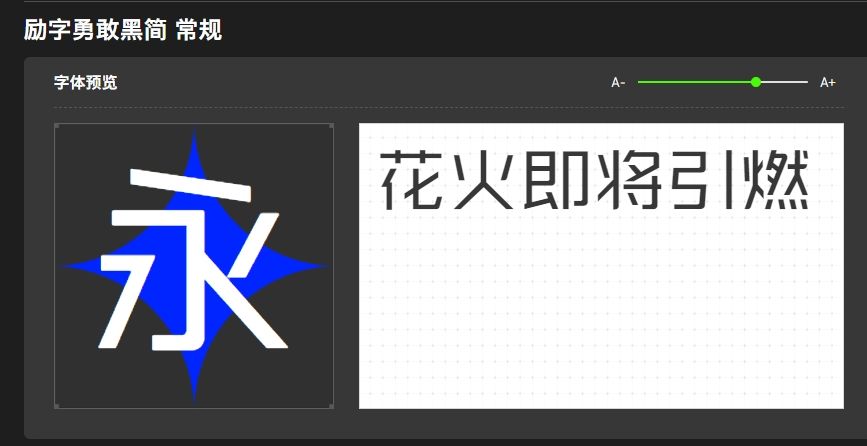
在品牌建设和推广过程中,字体的选择至关重要。一款合适的字体不仅能够准确传达品牌的形象和价值观,还能够增强品牌的识别度和记忆度。今天,就为大家推荐几款品牌都在使用的经典字体,为你的品牌设计提供灵感和参考。
励字励倩简作为中国传统的字体之一,具有古朴典雅的特点,以扁平硬笔的书写轨迹为基础,笔锋避免尖锐,设计成微小的圆弧,柔润舒畅,字型方正饱满;笔划粗细对比适中,婉转妩媚、温顺乖巧,看似平淡无奇,却能给人以美的感受。
励字勇敢黑简 常规是一种简洁明了的字体,具有鲜明的视觉冲击力。它的字形饱满、线条粗犷,能够给人一种现代、时尚的感觉。许多追求简约、前卫的品牌都选择使用黑体作为品牌字体,以展现其时尚、前卫的品牌形象。
除此之外,还有许多其他经典字体也被广泛运用于品牌设计之中。这些字体不仅具有独特的风格和特点,还能够与品牌形象相契合,提升品牌的整体形象和市场竞争力。